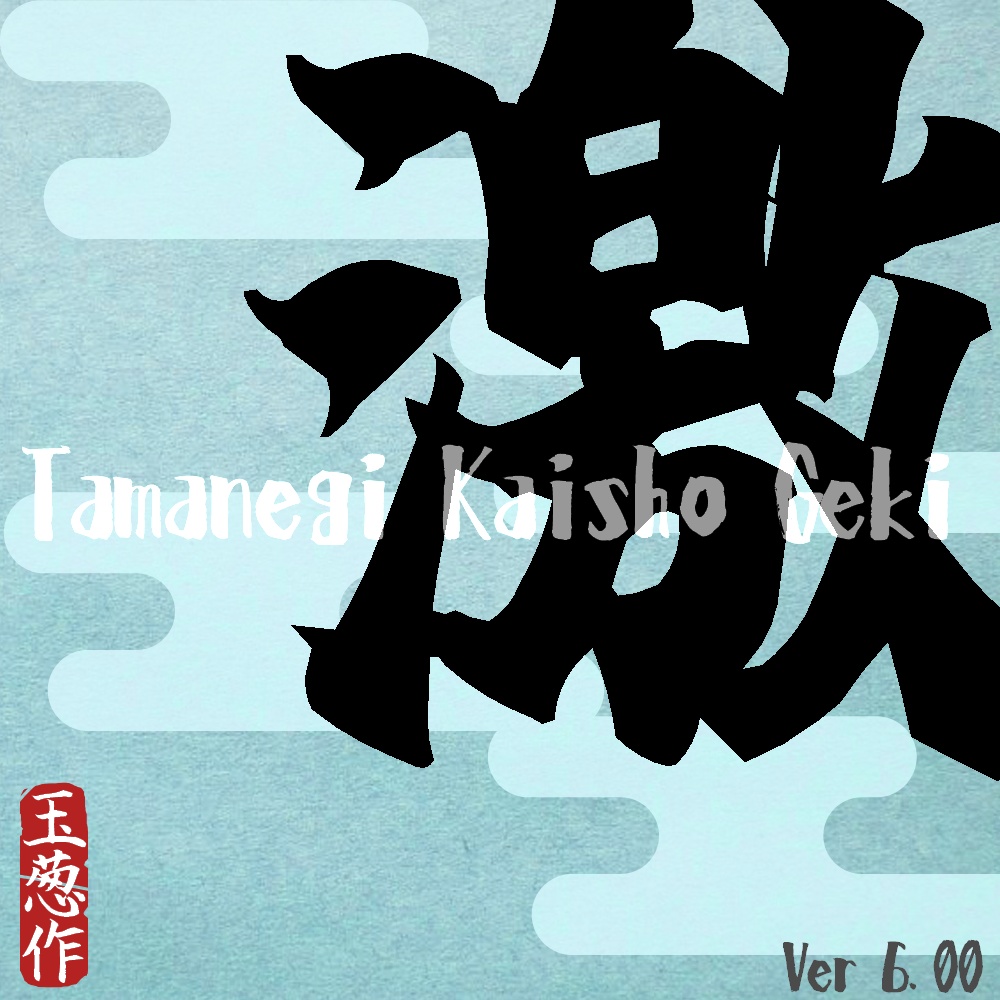
玉葱楷書激無料版v7
字体名称: 玉葱楷書激無料版v7
字体风格: 个性
玉葱楷書激無料版是简单的手写笔刷字体洋葱正本字体的稍微激烈的版本,它是为视频,同人志,新年贺卡等各种场景而创建的字体。
【收录文字】
• 345 个全角字符(平假名、片假名、012、ABC、abc、希腊语、俄语)
• 符号233字(?〆㈱【】{}@*※→†√⑳Ⅸ㌍㎞)
• 半角157个字符(ABCabc片假名!?*{} []./@#$%\)
• JIS一级汉字,共2965个字符
• 大约几个可能用于创作的汉字组合,您可以自行选择